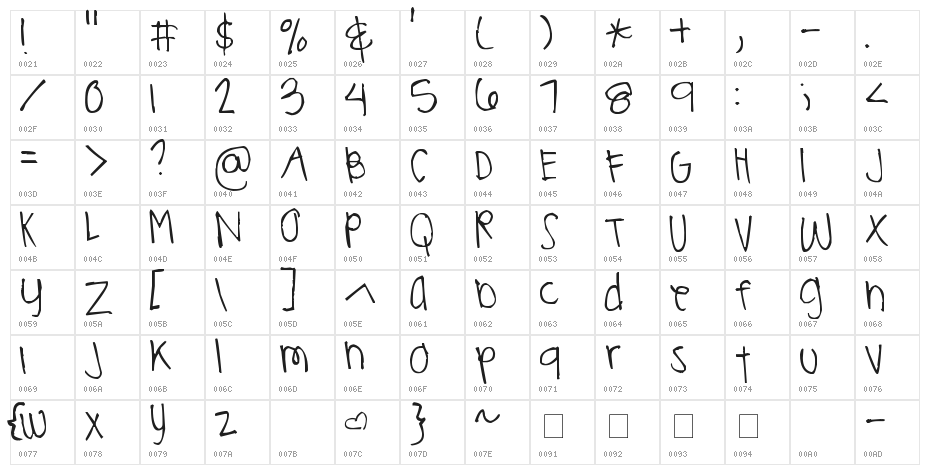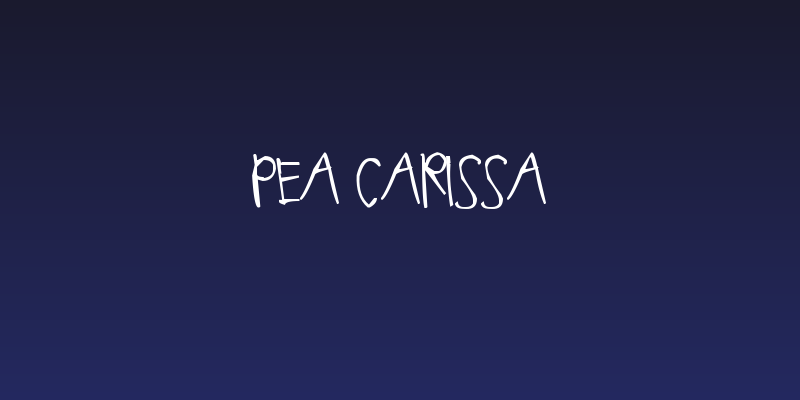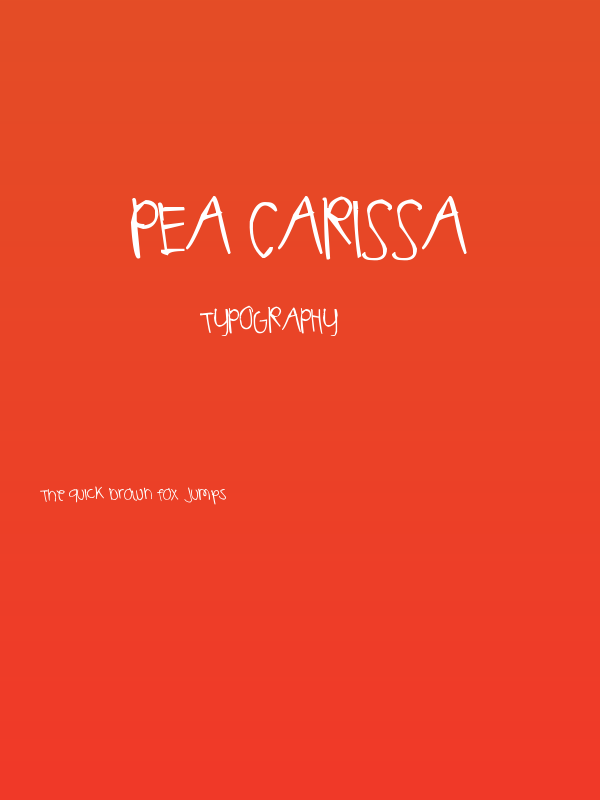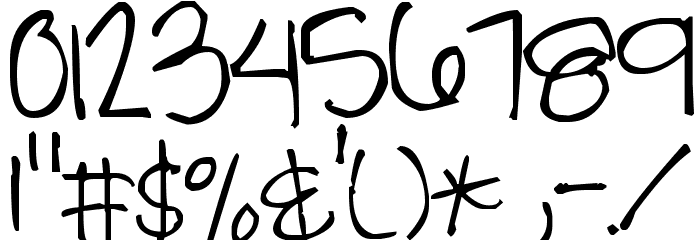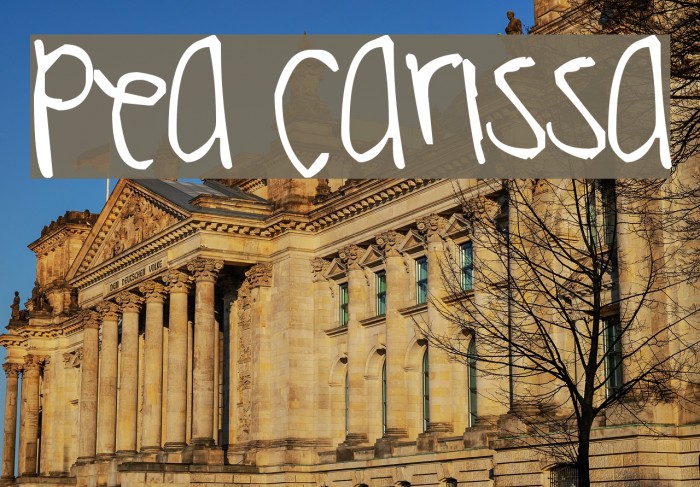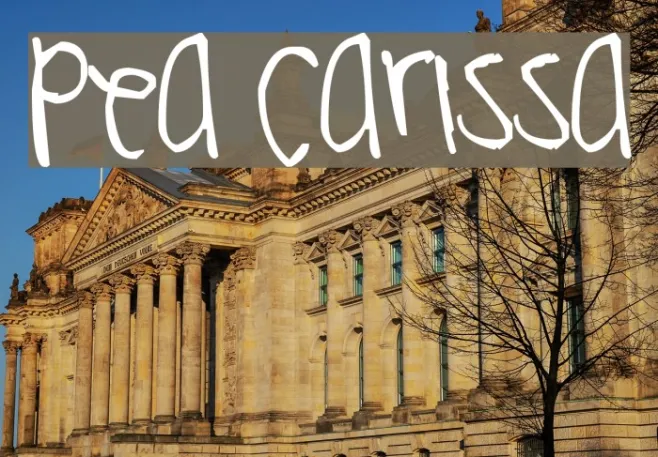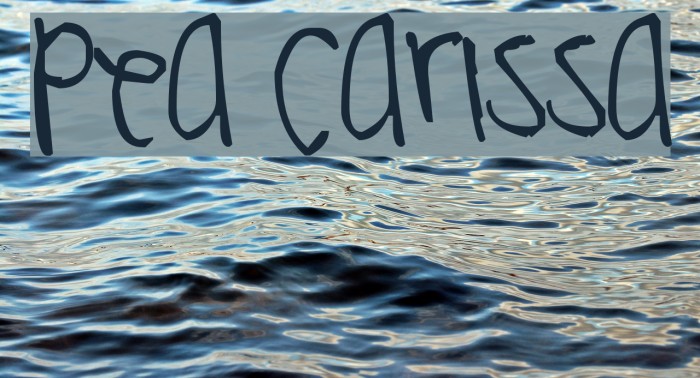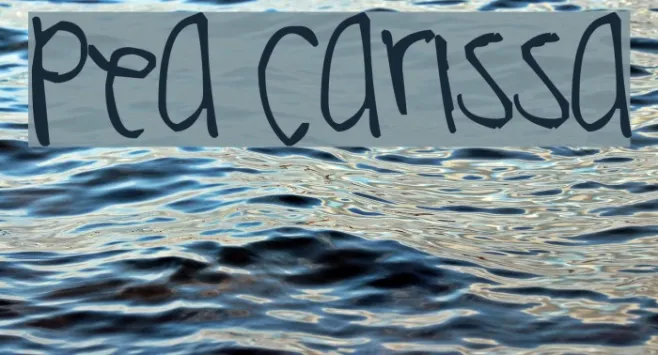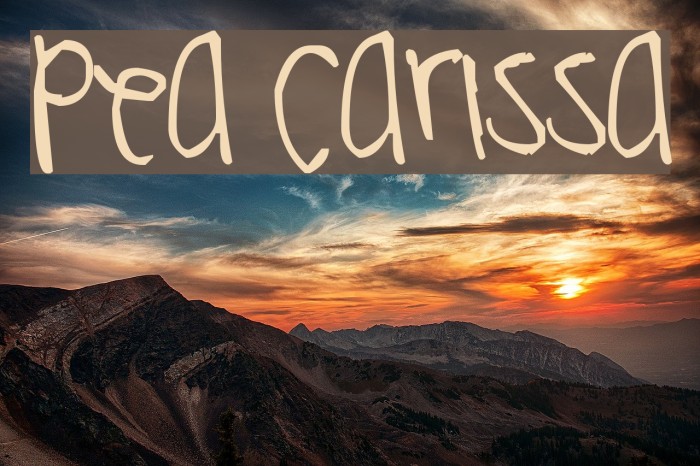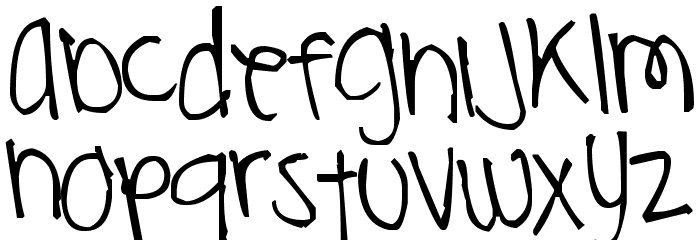
Pea Carissa Font
| Stile generale | Casual |
| Caso d'uso | Logos, Headlines, Informal Text |
| Progetti proposti | Ideal for greeting cards, personal notes, scrapbooking, and informal branding projects. |